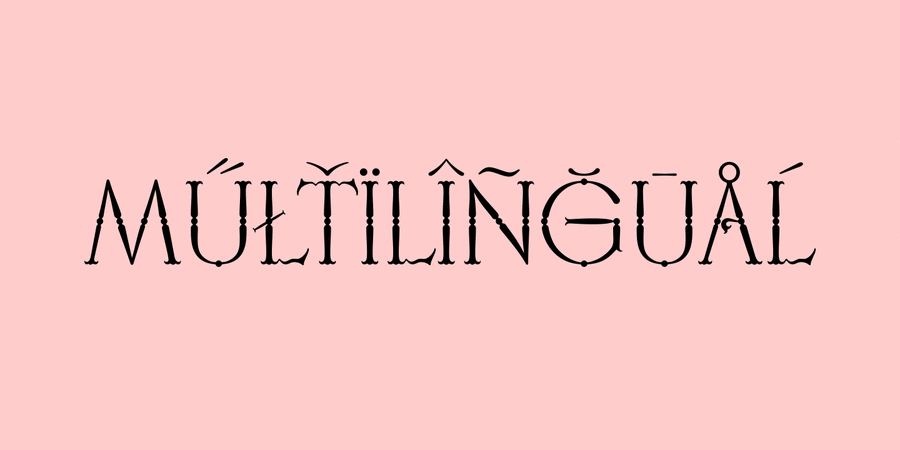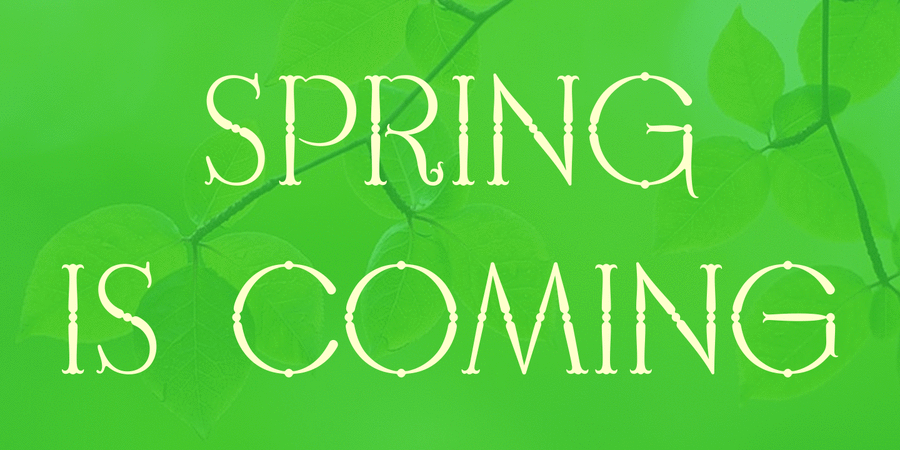
Франческа — вишуканий декоративний шрифт, відмінно підходить для урочистої та святкової продукції. Шрифт розроблено Лук'яном Турецьким у 2015 році.
Асоціації з сімейством шрифтів FrancescaОсобистість і характер гарнітури:
лицарський, старовинний, історичний, казковий, чарівний, химерний, вишуканий, вигадливий, потішний, майстерний, художній, благородний, ювелірний, грайливий, витончений, красивий, виразний, характерний, дзвінкий, прекрасний, ажурний, святковий, музичний, колоритний, смачний, урочистий, артистичний, королівський, елегантний, золотий, аристократичний, розкішний, багатий, романтичний, пристрасний, експериментальний
лицар, обладунки, сувій, музей, гравюра, мініатюра, мистецтво, історія, одяг, театр, казка, тату, татуювання, король, королева, прикраса, ювелір, дитяча книжка, кафе, десерт, геральдика, музика, Чарівна казка, ресторан, подарунки, коштовності, розкіш, антикваріат, булочна, кохання, вино, свято, романтика, сукня, замок, легенда, графіка, ілюстрація, люкс Гарнітура має ознаки стилів: